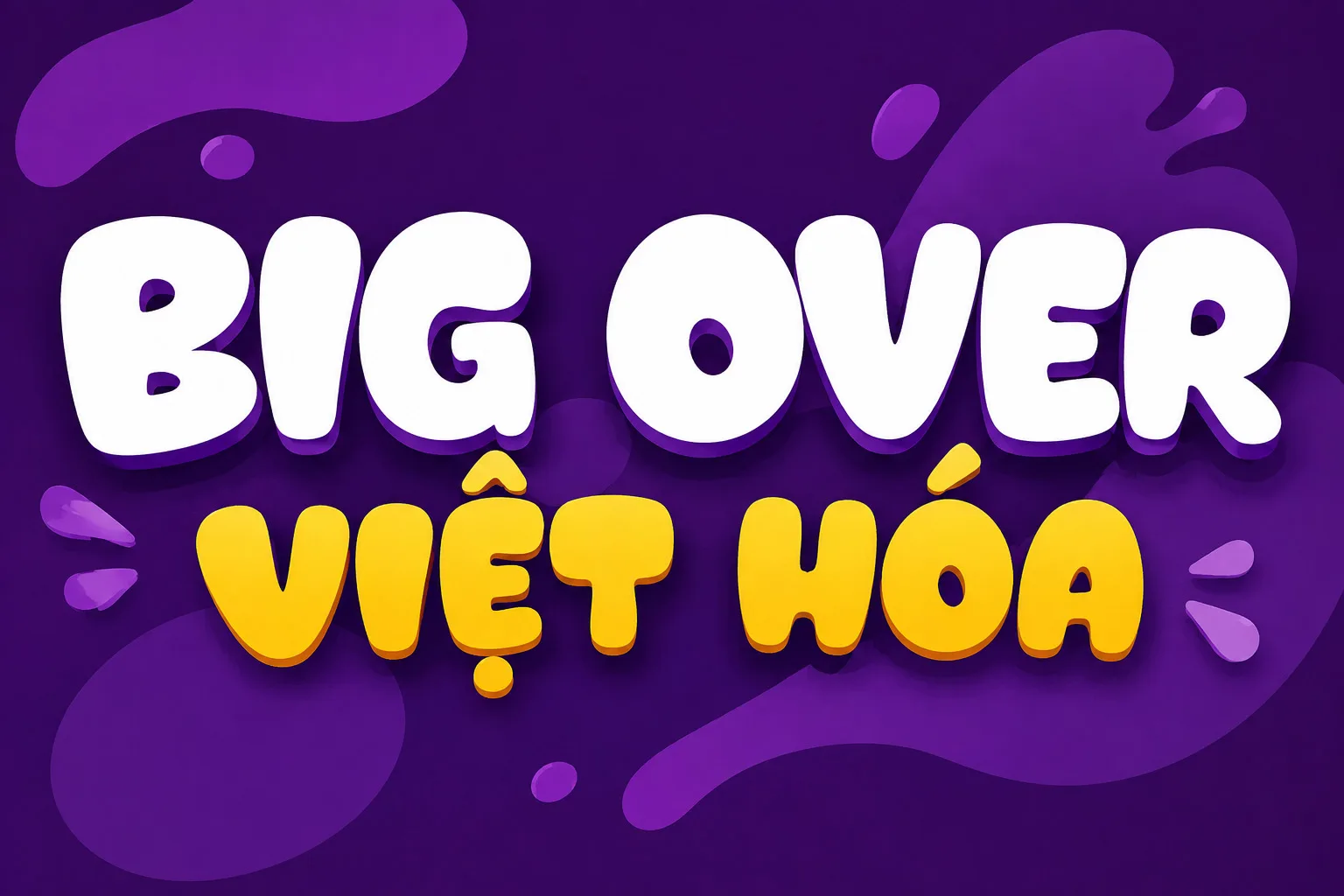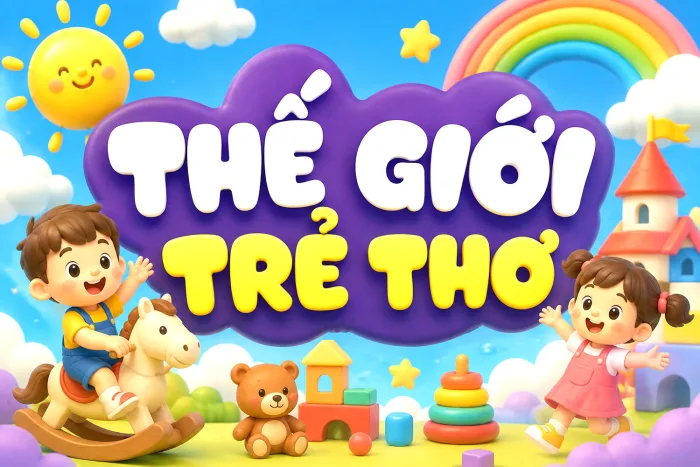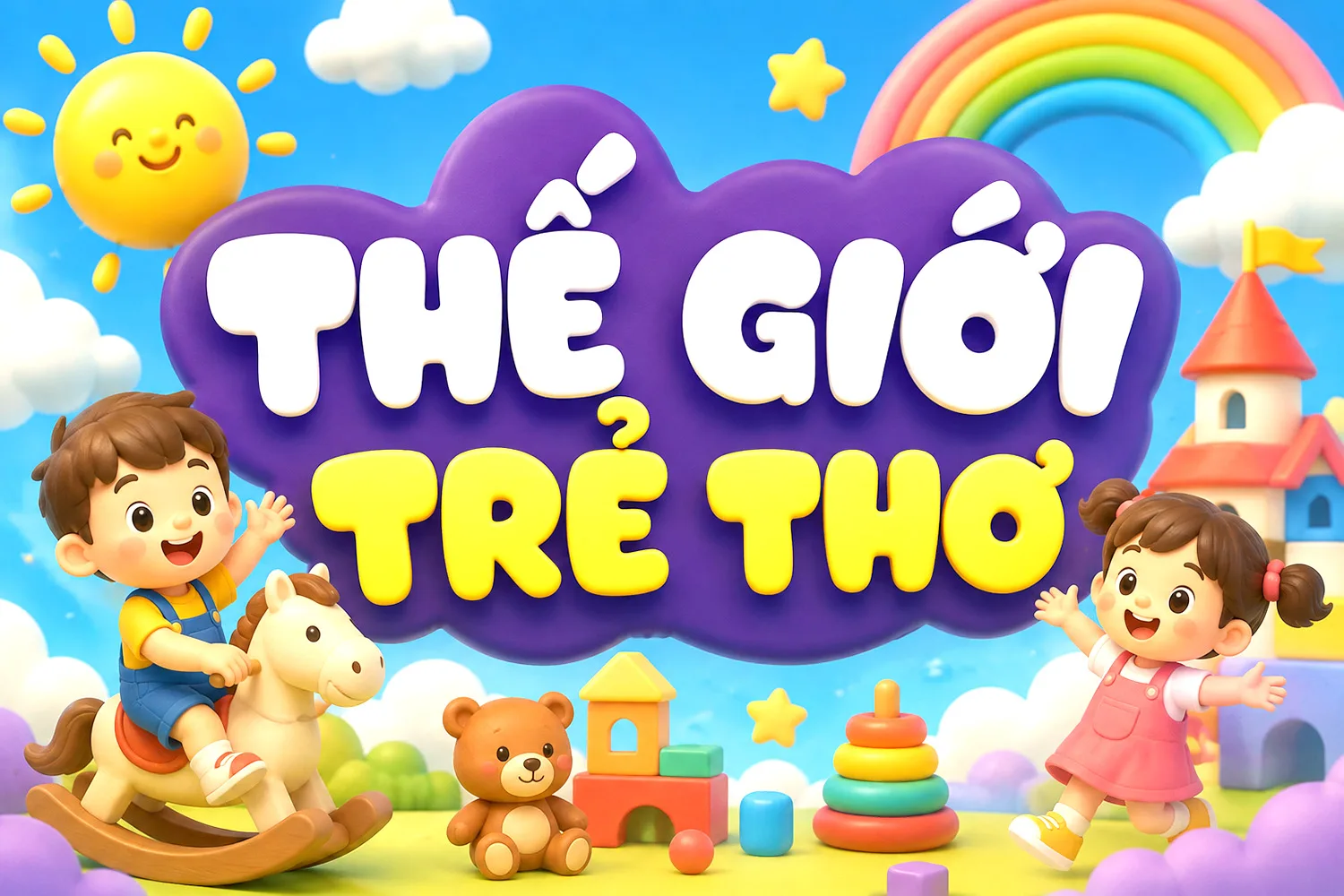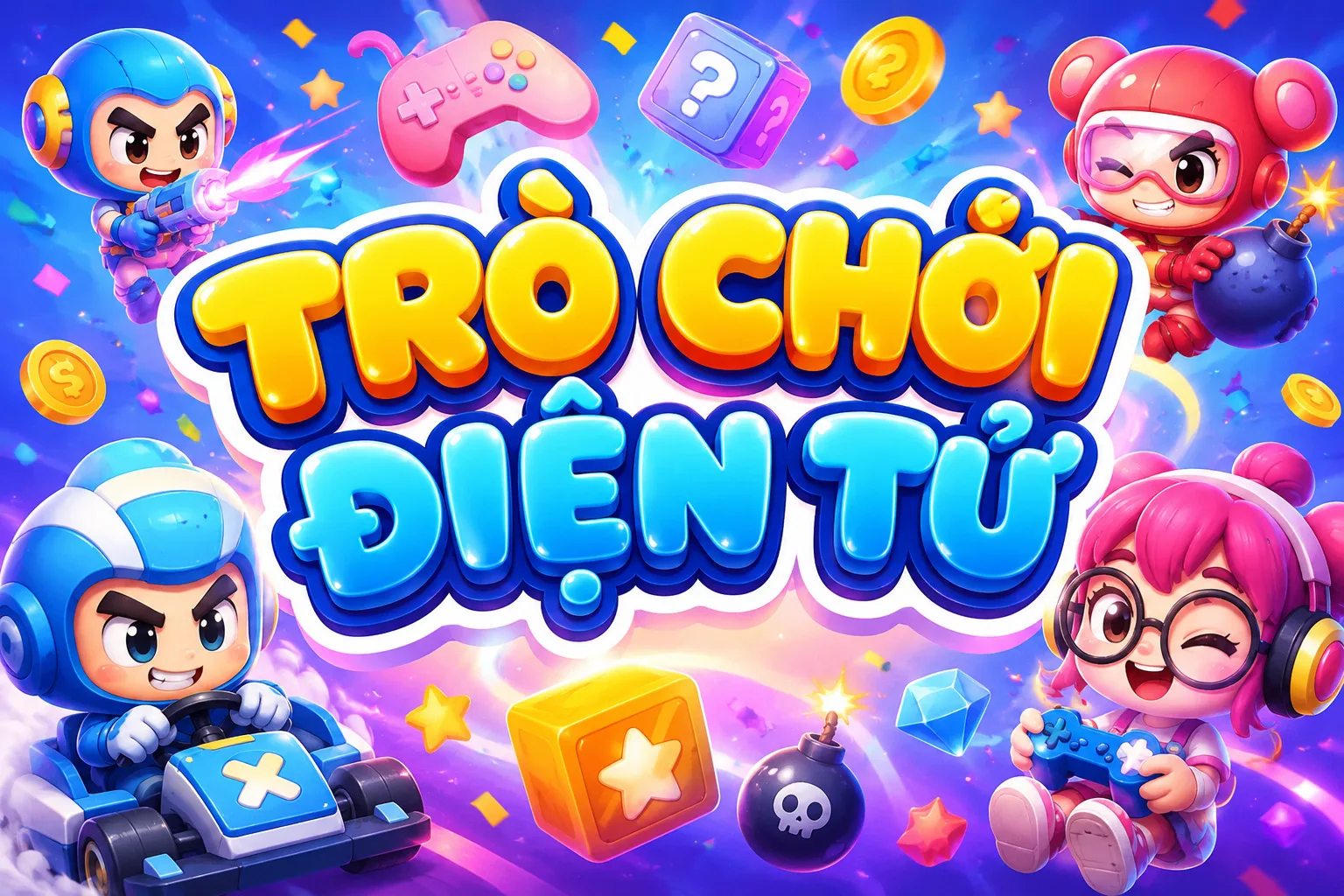
DVN Big Over Việt hóa – Font Display Béo Tròn, Ngộ Nghĩnh & Đầy Cá Tính
DVN Big Over Việt Hóa là phiên bản Việt hóa của kiểu chữ Big Over với phong cách display cực kỳ nổi bật: béo, tròn, mềm mại và vui nhộn. Các nét chữ dày, bo tròn mạnh cùng hình dáng organic tạo cảm giác thân thiện, trẻ trung và có chút playful.
Font đặc biệt phù hợp cho headline, poster, banner, thumbnail, social media, packaging, branding và những thiết kế cần một kiểu chữ thật bắt mắt ngay từ cái nhìn đầu tiên.
Phiên bản Việt hóa được tối ưu để hiển thị tốt với hệ thống ký tự tiếng Việt, giúp bạn dễ dàng sử dụng font cho các thiết kế nội dung tiếng Việt mà vẫn giữ được tinh thần nguyên bản của kiểu chữ.